2021 Police Tendances à utiliser par les designers cette année
En 2020, Clif Stoltze et Katherine Hughes, de Stoltze Design, nous ont parlé de la puissance des nouvelles polices de caractères expérimentales, des mises en page symétriques avec des écarts sélectifs et de la valeur des modèles classiques.
Gloria Kondrup, consultante en design et professeur à plein temps à l'ArtCenter College of Design, nous a encouragés à "ne pas jouer la carte de la sécurité typographique". Angie Wang et Mark Fox, partenaires du studio de design primé Design is Play, ont donné des conseils avisés sur l'utilisation d'une typographie brutale, d'un texte très lisible et de variables polices, afin de capter et de fidéliser le public.
Qu'en est-il du site Police Trends pour 2021 ?
Nous observons des tendances claires en matière de polices de caractères. Les écritures légères seront de plus en plus utilisées. En plus d'une nouvelle race de caractères sans empattement très prisés, les caractères sans industriels s'imposent. Le site Polices avec une fioriture est toujours d'actualité et les caractères d'affichage de poids élevé attirent l'attention.
Police Tendance n° 1 : les scénarios légers
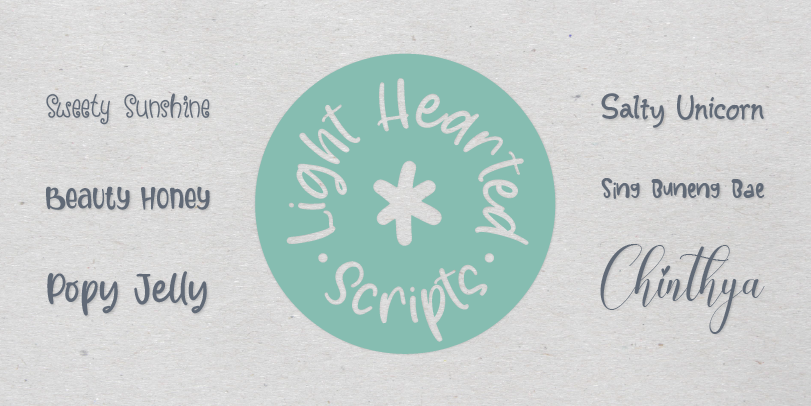
C'est peut-être en raison d'une vision optimiste de l'année 2021 que les écritures ludiques et légères sont de plus en plus utilisées. Elles ont une qualité d'écriture fraîche et leurs caractères aux formes libres et à l'épaisseur de trait inhabituelle confèrent à polices une nature irrévérencieuse et insouciante. Les marques pour enfants se prêtent naturellement à ces écritures spéciales. Leurs formes ludiques et arrondies sont idéales pour les produits destinés à un public plus jeune. Elles sont également très à l'aise dans les emballages, les couvertures et la conception éditoriale.
Sweety Sunshine est une bouffée d'air frais, ses lettres dansent sur la page avec une liberté enfantine, tandis que Beauty Honey combine des lettres majuscules et des lettres bi-formulaires dans un script amical et décontracté qui permet de créer facilement des logos distinctifs, des emballages puissants et des bannières qui attirent l'attention. Popy Jelly et Salty Unicorn pourraient être des frères et sœurs typographiques - ou du moins des cousins très proches. Ils célèbrent les charmantes bizarreries des lettres dessinées à la main, tout en étant énergiques et ludiques. Elles sont toutes deux idéales pour l'emballage, les annonces sociales et l'image de marque des jeux. Chinthya a juste une touche de formalité, mais n'est jamais guindé, tandis que Sing Buneng Bae tire parti d'une multitude de caractères alternatifs pour créer des titres et des logos uniques en leur genre.
Police Tendance n°2 : Sans avec une touche d'originalité
De nouveaux types de caractères sans empattement sont dessinés et attirent l'attention. Elles vont de la précision du télescope spatial Hubble à la forme libre et au romantisme sauvage. Toutes, cependant, reprennent la conception de base des caractères sans empattement et y ajoutent quelque chose de spécial.
La famille Hello Paris Sans est composée de cinq graisses de caractères tout en capitales avec des ligatures contextuelles et des lettres swash fluides en position shift. Le résultat est une confection typographique d'une remarquable polyvalence. La famille Compiler est composée de 32 dessins d'une apparente exactitude monospaciale - sauf qu'elle n'est pas monospaciale. Le Compiler possède les empattements vestigiaux typiques des dessins monospaciaux, tandis que le Compiler Plain en est dépourvu. La reconnaissance de la marque est garantie et les polices peuvent être utilisées pour les sites web, les applications, la conception d'entreprise, les rapports annuels, l'orientation, etc. Louisa, en revanche, est une véritable police monospaciale. Mais des caractères comme les minuscules a, e, g, k, v, w, x et y lui confèrent un aspect amical et accueillant. Les polices en italique ont également une base cursive. ToreTtO est un autre exemple de sans géométrique hautement structuré. Ses capitales et ses petites capitales inclinées vers l'avant permettent de créer des énoncés à la fois imposants et minimalistes dans les titres, sous-titres et sous-titres. dans les titres, les sous-titres, les affiches et les couvertures. Kutilang est un design condensé à taille haute, adouci par une subtile influence calligraphique. Il est polyvalent, peu encombrant et distinctif. Lunema porte les "pièges à encre" des années 1970 et 1980 à de nouveaux sommets. Bien qu'ils soient très visibles dans les grandes tailles, ils créent un aspect presque doux et fluide lorsque la taille du point est réduite. La queue du g et du y apporte un contrepoint tranchant à cette flexibilité implicite, ce qui en fait un dessin mémorable.
Police Tendance n° 3 : les swashs à profusion
Polices Les personnages de type "swash" existent depuis les années 1970, ils ne sont donc pas vraiment à la pointe de la mode.
Mais de nouveaux modèles sont ajoutés à l'offre de MyFonts presque quotidiennement. La plupart sont des versions modernes du genre des années 70, mais certains sont aussi nouveaux que demain.
Brande, Lotaline et Beauty Magnolia sont des designs à empattement lourd qui sont étonnamment légers, tandis que Brastika est composé de neuf poids de formes de lettres fluides. Les graisses les plus légères et les plus grasses créent des bannières et des titres attrayants, tandis que les graisses moyennes sont parfaites pour les liens de navigation et les sous-titres. Cherlynda est une écriture fluide idéale pour créer des invitations, des titres publicitaires, des emballages de produits et des affiches pour des événements spéciaux. Stephen est une autre écriture fluide avec une abondance de variantes de swash, tandis que Megilan est une écriture douce sans empattement avec des fioritures extraordinaires.
Police Tendance n° 4 : Industrial Strength Sans
Les caractères sans empattement de qualité industrielle se distinguent par leur puissance directe et la durabilité de leur conception. Ils peuvent être utilisés dans une grande variété d'applications et avec l'assurance qu'ils ne paraîtront pas démodés.
Brahma est un sans géométrique affirmé de neuf graisses qui convient aux étiquettes imprimées, aux bannières numériques et à presque tout ce qui se trouve entre les deux. Revx Neue, et son compagnon Revx Neue Rounded, forment une grande famille de caractères sans empattement carrés, aussi à l'aise à l'impression qu'à l'écran. La famille Panton ne peut être décrite que comme massive. Un autre design à épaules carrées qui ne semble pas avoir de limites, c'est un investissement typographique qui se rentabilisera plusieurs fois. Trade Gothic Suivante est une réimagination de la quintessence de la force industrielle sans empattement. Tout aussi puissante que la version originale, la nouvelle version est encore plus polyvalente. Dredger et Roadhouse sont des caractères d'affichage qui résisteront facilement à l'épreuve du temps.
Police Tendance n° 5 : conception de présentoirs lourds
Il s'agit de caractères d'affichage à poids unique qui ont de la présence et du caractère. Leurs proportions généreuses et leur caractère ludique en font des caractères exceptionnels pour les grandes tailles.
Estika, Jane Frediction, Salty Candy et Tahu Bullats sont des textes - chacun avec un comportement différent. Estika est immédiat et un peu nerveux, tandis que Jane Frediction est folklorique et amical. Salty Candy a une naïveté fraîche et Tahu Bullats a une écriture de peintre d'enseignes, presque droite. Eugello et Geeki sont des caractères à empattement au charme pesant. Tous ces caractères constituent des bases parfaites pour les affiches, les logos, les titres imprimés, les bannières numériques et tout autre endroit où l'on a besoin d'un caractère qui se démarque et qui se porte bien.